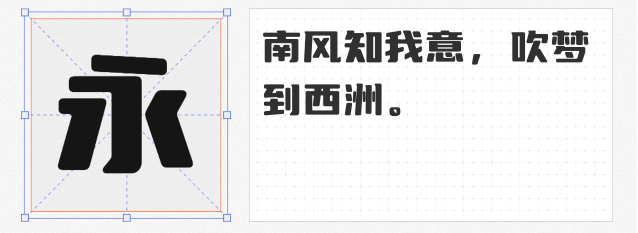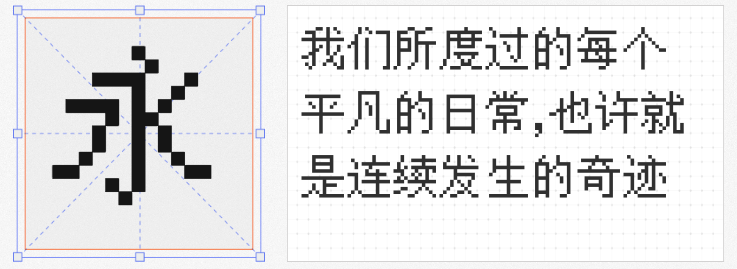
在电影视觉设计中,字体不仅是信息传递的载体,更是氛围营造的关键元素。以下四款免费商用字体,凭借独特的设计语言与电影场景的高度适配性,成为大银幕上的“无声演员”。
作为优设标题黑的衍生字体,优设标题圆将尖锐的棱角转化为圆润弧线,在保留力量感的同时增添柔和气质。其笔画粗细对比强烈,中宫开阔,适合科幻片标题、未来感字幕或动画电影的动态呈现。圆角设计既能弱化攻击性,又能通过几何结构传递科技感。
这款字体以“追光”为概念,通过圆弧转角与包围结构切口的创新设计,赋予文字动态张力。中宫宽大的字形结构确保远距离可读性,适合青春片、运动题材或游戏改编电影的片头字幕。其笔画末端微妙的倾斜角度,能强化画面速度感。
融合传统篆刻的“刀痕”笔触与现代圆角设计,仓耳与墨 W04创造出“内方外圆”的独特美学。这款字体适合历史题材、武侠片或文化纪录片,其刻痕质感可呼应古代碑文或竹简纹理,而圆角处理则避免视觉过于生硬。在战争场景的字幕中,刀刻笔触能强化史诗感,而圆角转折又暗含人文温度。
作为专为屏幕优化的点阵字体,文泉驿点阵宋体以13px字号呈现清晰锐利的显示效果,适合复古科幻、悬疑片或像素风动画。其严谨的网格结构与宋体骨架,能完美复刻早期电子屏幕的机械美感。